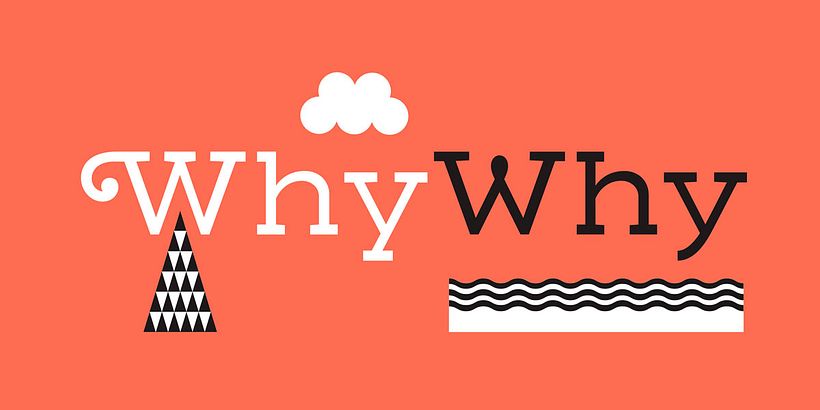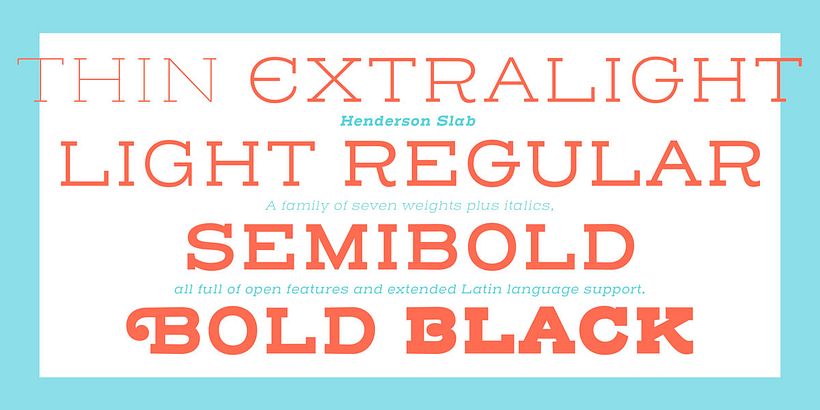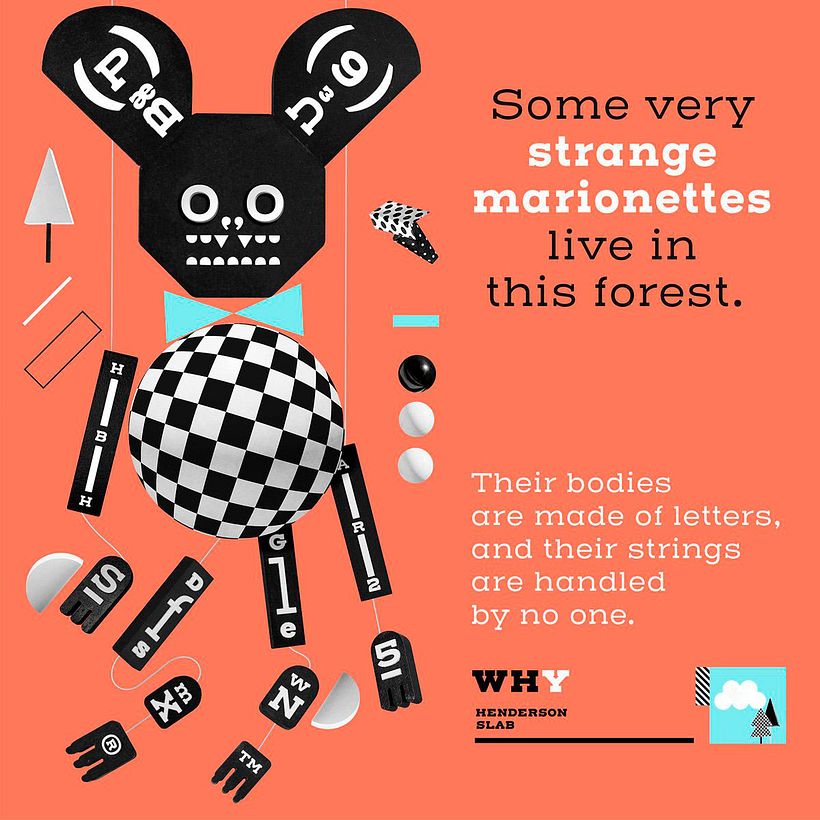
Érase una vez... la tipografía Henderson Slab
Resulta inusual encontrar proyectos tipográficos integrales tan inspiradores como el llevado a cabo por Cinco y Ale Paul.
Es por eso que llama tanto la atención el modo que han ideado estos argentinos para presentar uno de los últimos lanzamientos de Sudtipos: la tipografía Henderson Slab. La tipografía, por sí misma, ya tiene un carácter bastante marcado, pero el equipo de Cinco ha logrado imprimirle un plus de singularidad al crear un poster plegable en el que unas marionetas con cuerpo tipográfico son las protagonistas.
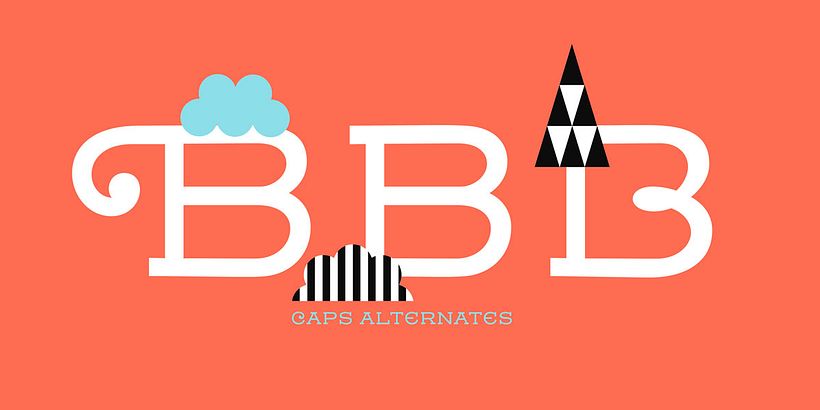
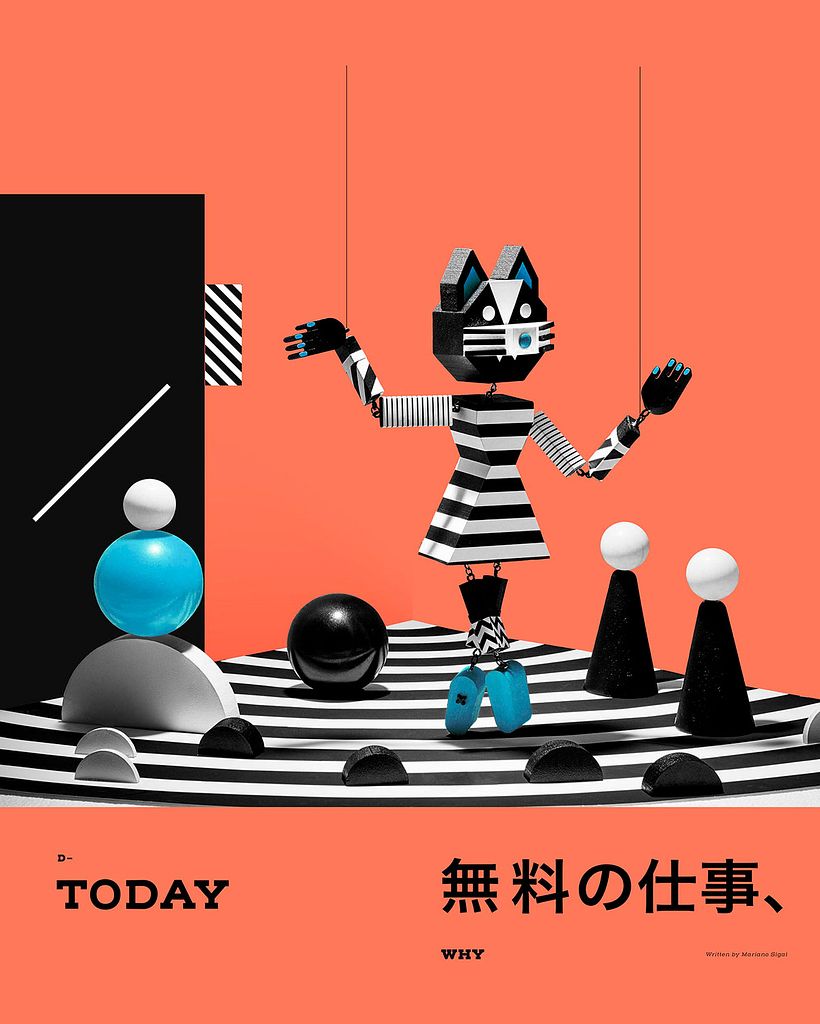Érase una vez... la tipografía Henderson Slab 1
Érase una vez... la tipografía Henderson Slab 2
Érase una vez... la tipografía Henderson Slab 3
El proyecto, basado en un cuento ideado y escrito por el propio estudio creativo, sirve como excusa para mostrar y utilizar algunas técnicas que sus creadores adoran, pero cuya utilización no suele ser tan común en algunos aspectos del diseño: character design, paper craft, marionetas y fotografía.
Some very strange marionettes live in this forest. Their bodies are made of letters and their strings are handled by no one.
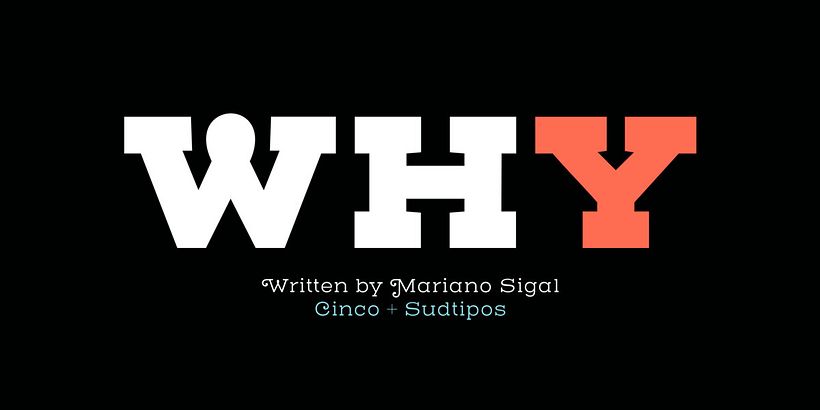Érase una vez... la tipografía Henderson Slab 5
Érase una vez... la tipografía Henderson Slab 6
Érase una vez... la tipografía Henderson Slab 7
Una curiosa y creativa manera de promocionar una tipografía utilizando disciplinas creativas que, a priori, nada tienen en común con el tema principal. Un ejemplo perfecto del talento y creatividad sin límites imprescindible en estos tiempos en los que el mundo de la tipografía comienza a desplegar de nuevo sus alas y a cobrar importancia.
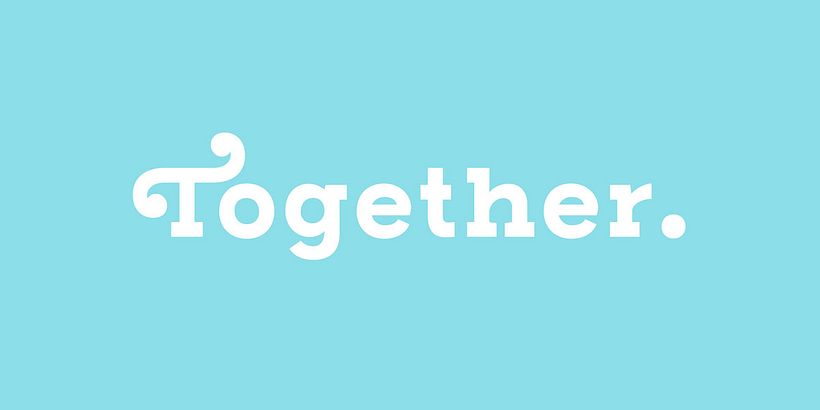
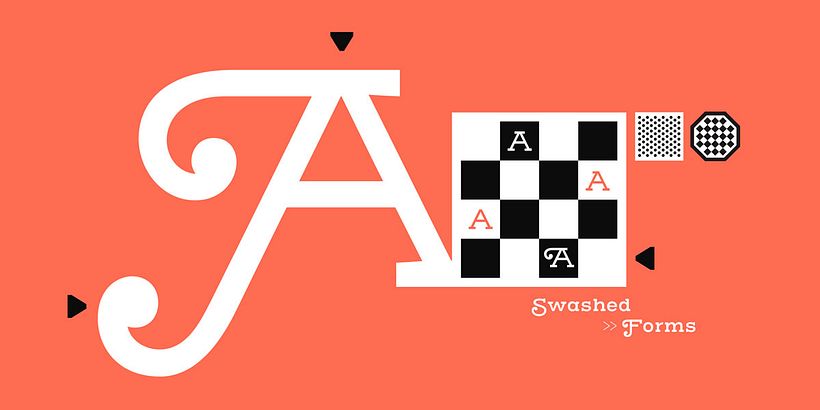Érase una vez... la tipografía Henderson Slab 9
Érase una vez... la tipografía Henderson Slab 10
Érase una vez... la tipografía Henderson Slab 11
Érase una vez... la tipografía Henderson Slab 12
Érase una vez... la tipografía Henderson Slab 13
Érase una vez... la tipografía Henderson Slab 14
Detrás de esta idea están Ale Paul, diseñador de la tipografía Henderson Slab y el estudio creativo Cinco.